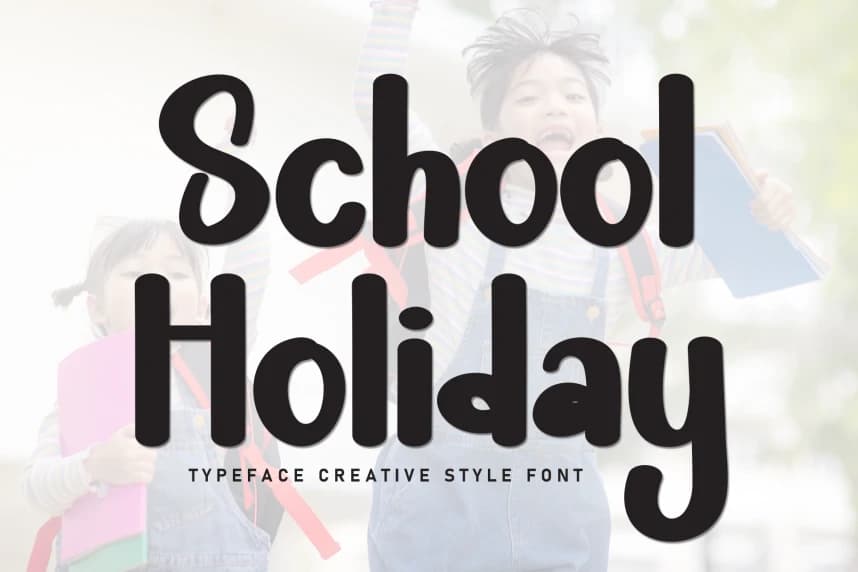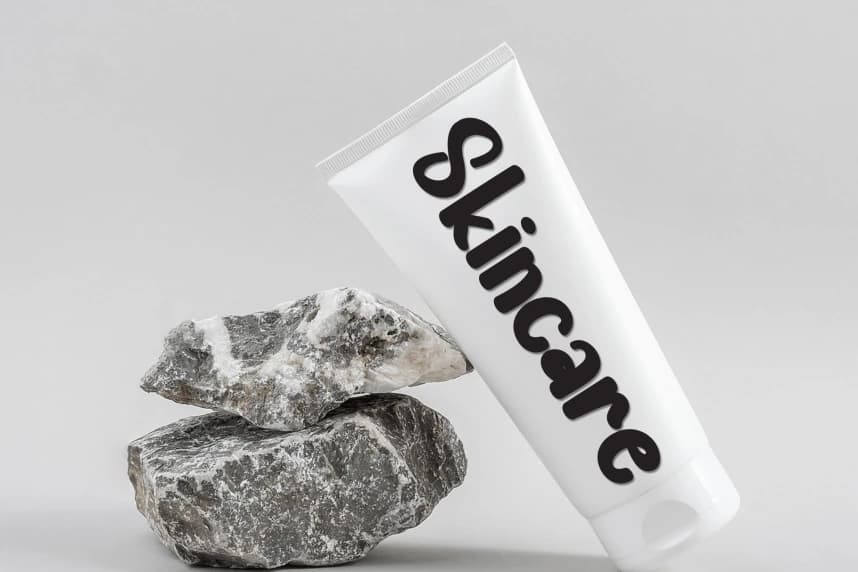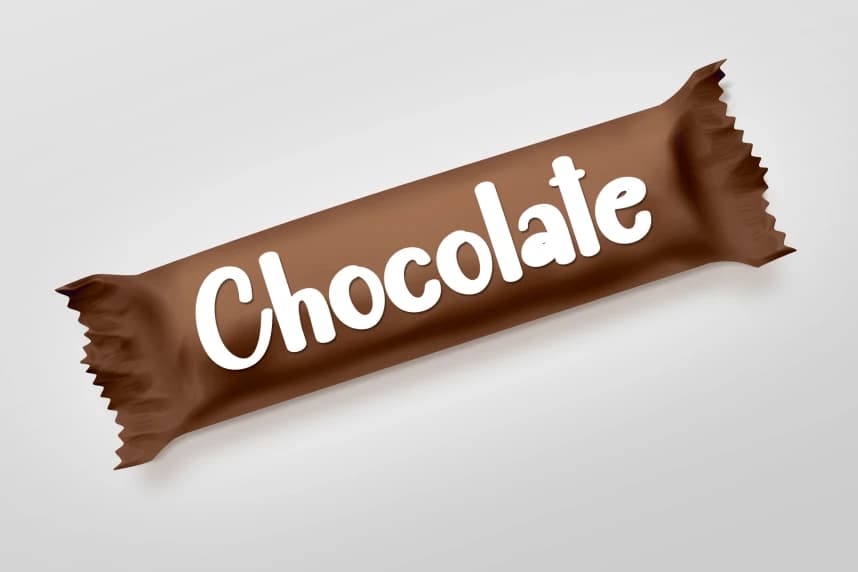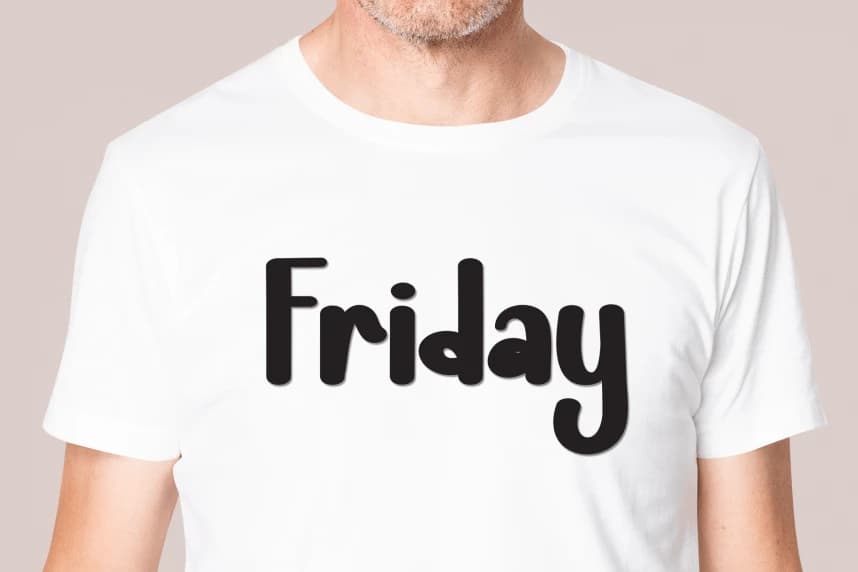
School Holiday – Creative Style Font
School Holiday – Creative Style Font, tatlı ve samimi bir el yazısı gösterim yazı tipidir. Sevimli ve eğlenceli olan bu yazı tipi, düğün davetiyelerini yazmak için, kartlar için ya da oyuncu bir dokunuşa ihtiyaç duyabilecek herhangi bir tasarım için idealdir.
School Holiday – Creative Style Font tatlı ve dost canlısı bir el yazısı gösterim fontudur. Sevimli ve eğlenceli olan bu font, düğün davetiyelerinin yazımı, kartlar veya herhangi bir tasarım için eğlenceli bir dokunuşa ihtiyaç duyulduğunda idealdir!
School Holiday – Creative Style